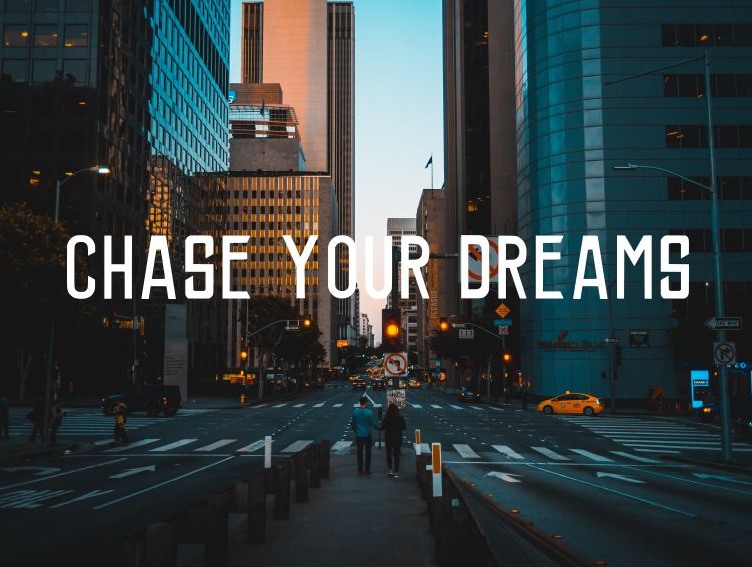
Aqui está uma versão breve e envolvente da descrição para a página de download da fonte ‘Flash Font Free’, focada na categoria Serif: ‘Em um mundo onde diferentes estilos de fontes são como luzes no escuro, Flash Font Free surge como uma elegante parada luminosa. Inspirado pelo designer mhdafifersya, essa serif é mais do que simplesmente uma ferramenta de escrita; ela transmite uma paixão por detalhes e um sentido de estilo. Moldada para quem aprecia o charme rústico da tipografia serif, Flash Font Free traz uma complexidade gráfica envolvente. Seja em cartazes de eventos ou em textos profissionais, essa fonte oferece um equilíbrio perfeito entre modernidade e sofisticação. Parabéns ao designer por criar algo tão belo e funcional. Flash Font Free é uma escolha imperdível para qualquer projeto que valorize a elegância dos estilos serif.’
Designer: mhdafifersya